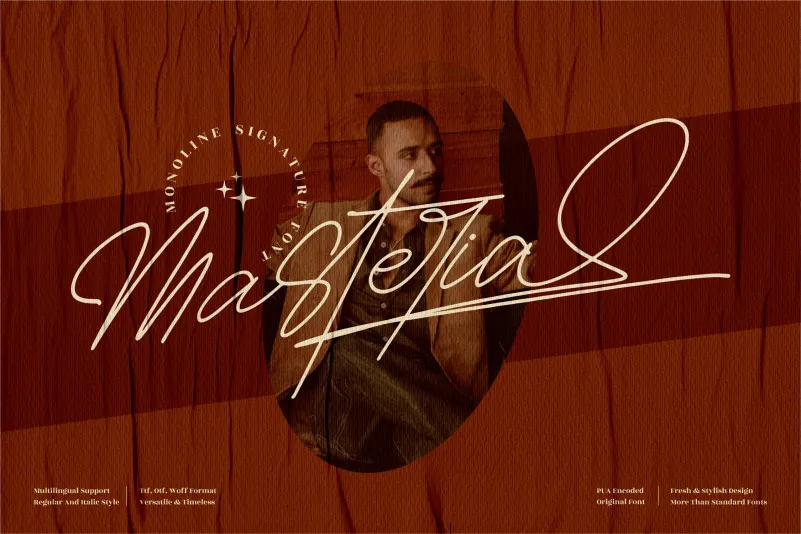
Masteria Font é uma elegante fonte script projetada para transformar qualquer projeto em algo excepcional. Suave e sofisticada, ela se adapta perfeitamente a uma ampla gama de aplicativos, desde logotipos e identidade visual até embalagens de produtos, revistas e materiais promocionais como tags, carteirinhas de visita, cartões de aniversário e até mesmo em mensagens de vídeo. Suporte para o Masteria Font é perfeito para quem busca um toque premium em sua arte digital ou impressa, garantindo que cada projeto seja apresentado com a dignidade e classe necessárias para os mais altos níveis de qualidade. Ideal para designers de marca, produtores de design gráfico e estilistas de moda, Masteria Font oferece o estilo necessário para alcançar qualquer objetivo criativo de alto padrão.